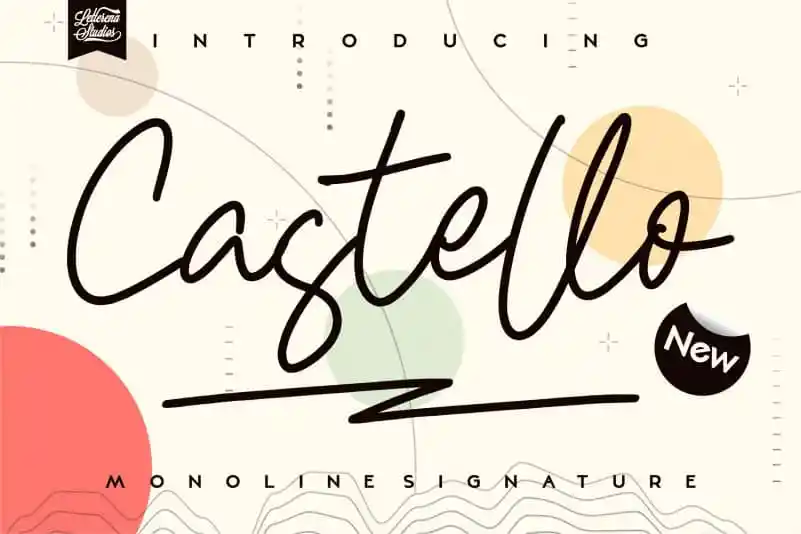
Castello Handwritten Font – Download Grátis
A Castello Handwritten Font é uma escolha perfeita para aqueles que valorizam o delicado equilíbrio entre modernidade e elegância na tipografia. Esta fonte handwritten é leve, mas ao mesmo tempo clássica, ideal tanto para projetos visuais pessoais quanto para aplicações industriais como marca identidade, embalagens de produtos ou até mesmo cartões de visita. Seu design fluido oferece um toque sofisticado que se adapta perfeitamente a uma variedade de recursos gráficos, desde cenas de eventos especiais e capas de livros até logotipos e texturas de imagem. Com sua presença minimalista porém poderosa, a Castello Handwritten é uma fonte ideal para criar um design único que se destacará em qualquer projeto. Seja você designer ou profissional da marca, a Castello Handwritten oferece a oportunidade de incluir seu toque pessoal e inovador na produção visual de seus projetos, garantindo um resultado profissional e atemporal ao mesmo tempo.